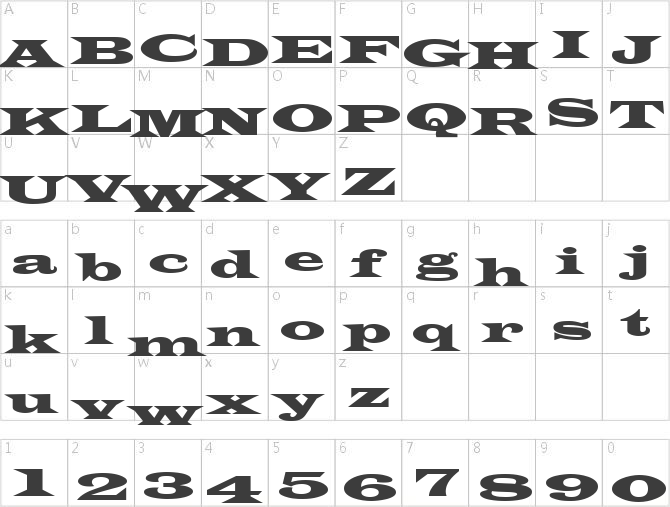
Latin-WideExt-Normal 詳情頁(yè)
Latin-WideExt-Normal字體字庫(kù)是一款讓人賞心悅目、百看不厭的英文字體,適合各類廣告和產(chǎn)品包裝設(shè)計(jì)應(yīng)用,字體大小0.04MB,格式為ttf字體,上傳用戶是lvpyt,作者/版權(quán)方為未知